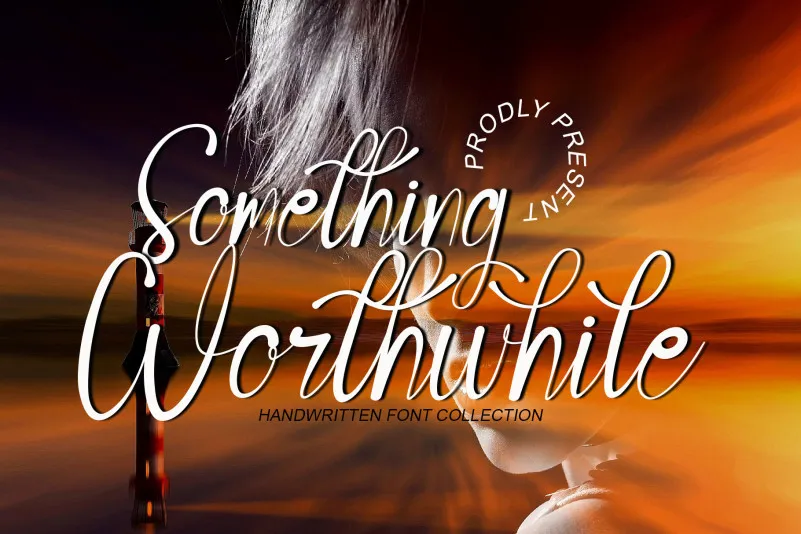
Something Worthwhile Font
A Something Worthwhile Font é uma escolha perfeita para quem procura uma fonte que transmite leveza e bom humor, sem perder a elegância que caracteriza os scripts. Com um tema descontraído e estilo refinado, esta font se destaca como uma ferramenta valiosa para qualquer biblioteca de fontes. Independente do assunto ou projeto, ela tem o poder de transformar qualquer criação em algo extraordinário, elevando-a a outro nível. Seja para cartões personalizados, design editorial ou até mesmo aplicativos, Something Worthwhile Font é uma opção ideal para aqueles que buscam um toque único e envolvente em suas produções visuais. Ideal tanto para os designers que procuram diversidade quanto para aqueles que buscam aperfeiçoar seus trabalhos com uma nova fonte, esta escolha se destaca como uma excelente adição à sua biblioteca de recursos gráficos.